中国汉字形式变化多样,各种字体都有一些拥护者和爱好者,历史久远的小篆当然不缺乏爱好者,即使它的历史已经很久远,在现在也仍然受到了大众的欢迎,广泛流传着。小篆由于其可变化性也出现了许多不同的小篆字体大全。
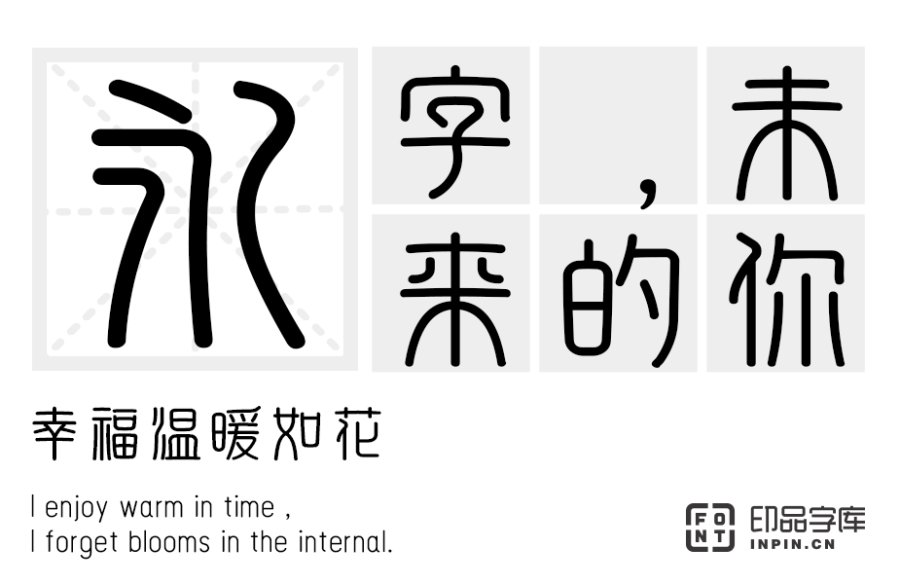
小篆在秦时就出现了,并且一直在几千年的历史长河中经久不衰。这里,小编为您稍微介绍一下小篆的特点。首先小篆的字形看起来十分优美,具有相对平衡对称的空间美感,因此自古至今都是书法家的宠儿。其次小篆的笔画相对复杂,也并不像我们平常书写的字体那么平直,也没有“横平竖直”的特征,而正是这种比较古怪的字体样式,在现代风盛行的今天也是显得愈加优美有特点。
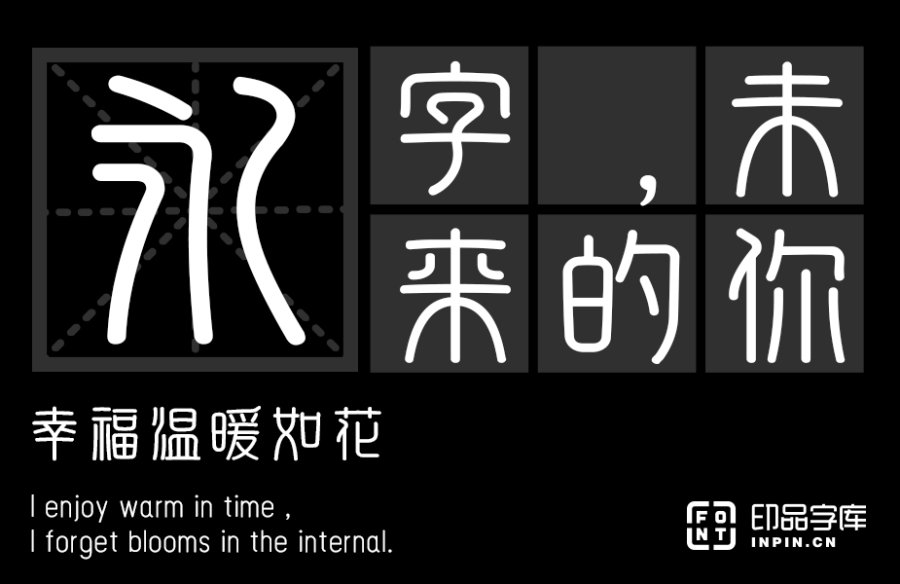
虽然小篆是一种字体,形式多变,也没有哪种最好看的说法,只是各有各的特点。但之前印品字库也有出过一款印品篆遇简,当篆体遇上简体,会擦出怎样的话火花呢?由于小篆字体的多变性,也有许多的小篆字体大全出现,不过哪种最好还是要结合个人的喜好来选择,毕竟各有所好嘛。如果想要设计自己喜欢的小篆字体,印品字库可以提供高端定制化服务,为个人、为团体设计独特的印章小篆字体。所以,对于哪种小篆字体最好看,大家也不能以偏概全,还是应该从个体出发,灵活选择。